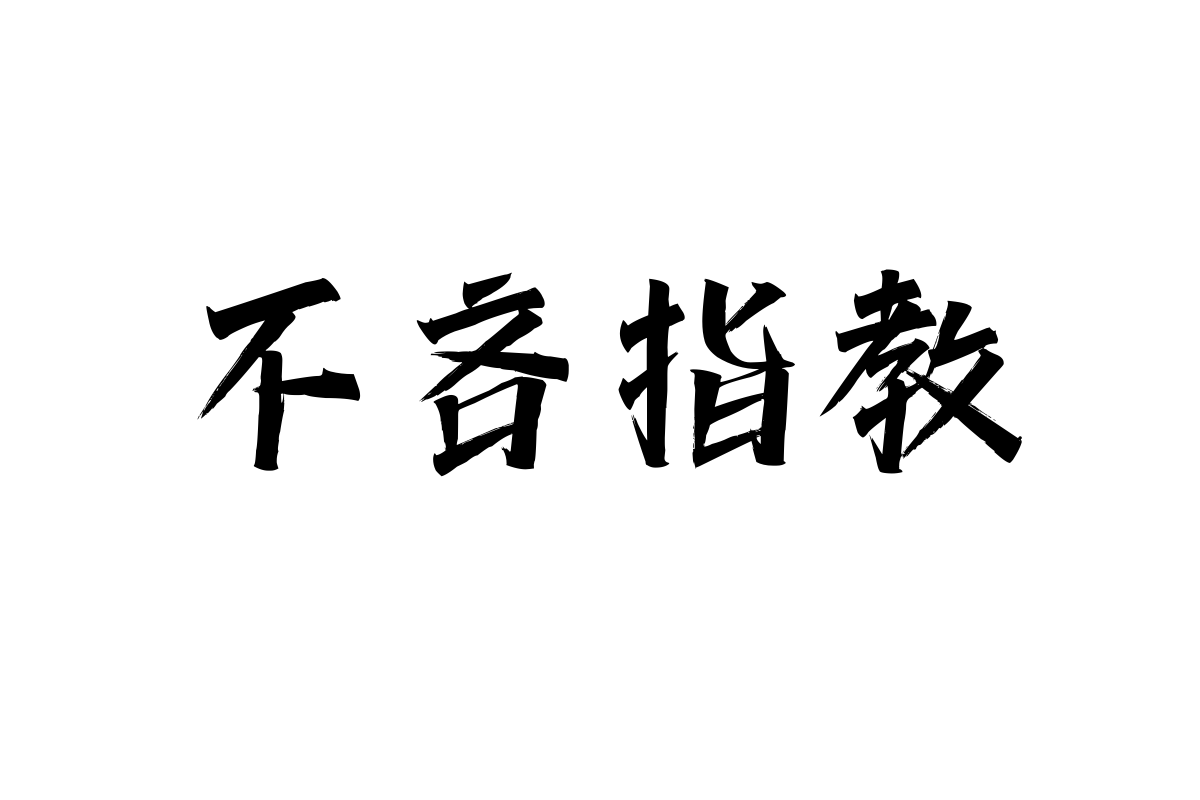
上首锋芒体是一种独特的字体,其特点是笔画尖锐、有力,给人一种锋利的感觉。这种字体在设计中常用来表达强烈的个性和独特的风格,如标题、标志等。上首锋芒体的特点是笔画粗细变化明显,线条流畅而有力,给人一种锐利、动感的感觉。同时,由于其笔画的尖锐性,也使得整体的视觉效果更加突出,能够更好地吸引人们的注意力。